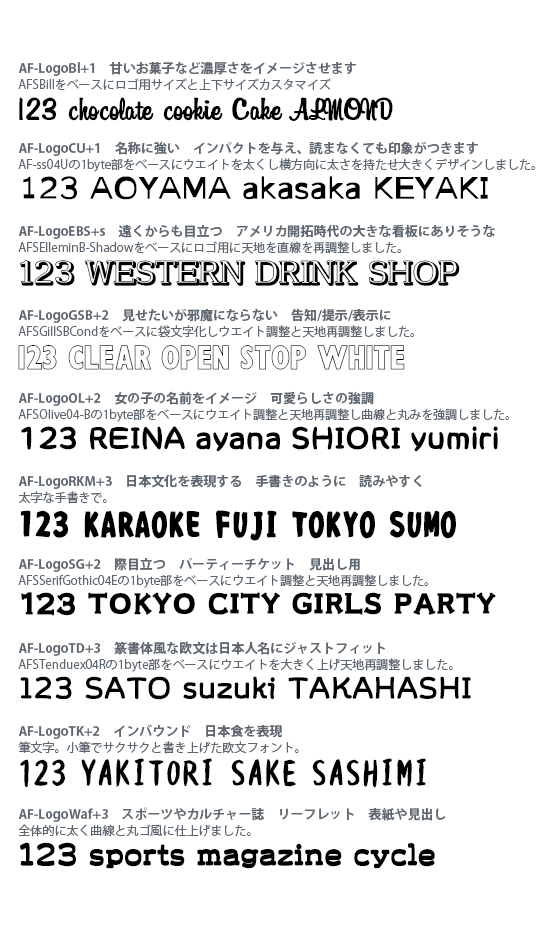
【収録書体】
AF-LogoBl+1
AF-LogoCU+1
AF-LogoEBS+s
AF-LogoGSB+2
AF-LogoOL+2
AF-LogoRKM+3
AF-LogoSG+2
AF-LogoTD+3
AF-LogoTK+2
AF-LogoWaf+3
半角アルファベット大文字小文字と数字からなる欧文フォントでやや太めのウエイトにデザインされました。
アウトライン抽出後自由にカスタマイズ、見出しやリードにもご利用頂けます。